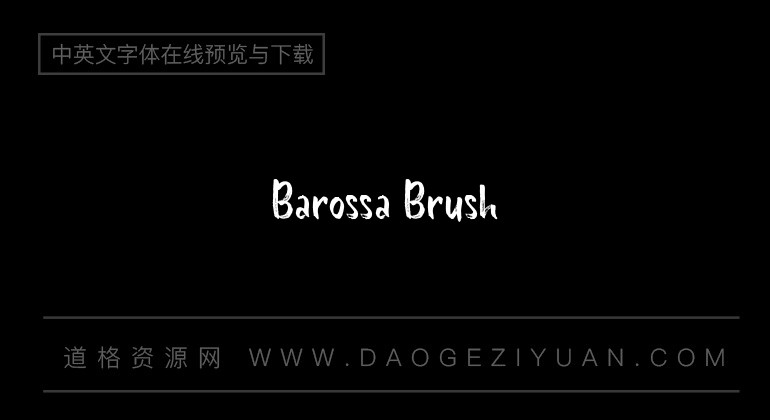
Barossa Brush 是一款粗体手写字体,它具有独特的风格,充满活力,可以用于商业和个人用途。它具有柔和的质感,可以为文字添加更多的活力和个性。它有多种字形,可以满足不同设计师的需求,并且可以轻松地在任何设计中使用。Barossa Brush 是一款非常适合用于现代设计中的字体,可以为设计师提供更多的灵活性和创造力。内容介绍
Barossa Brush是一款非常不错的手写艺术字体,具有很好的视觉感,适合于文化类的宣传设计、商业类品牌的广告和产品包装设计以及个性化文字排版等较多场景。